Neue Kindle Schriftart „Bookerly“ bald auch auf eReadern?
Amazon war in der Vergangenheit nicht nur immer besonders stolz auf die Hardware der eigenen Kindle eBook Reader, sondern hat auch die besondere Anpassung der Schriften hervorgehoben. So sollen die einzelnen Schriftarten allesamt besonders optimiert sein, um das Leseerlebnis noch weiter zu verbessern.
Tatsächlich bietet Amazon mit den vorinstallierten Schriftarten eine durchaus angenehme Ablesbarkeit der E-Ink Displays, was mitunter auch daran liegt, dass die Fonts vergleichsweise dick sind. Das ist wohl dem Umstand verschuldet, dass der Kontrast eines handelsüblichen E-Paper Bildschirms (selbst mit modernster Technik) einfach niedriger ist, als beim Tablet oder auf Papier (natürlich beleuchtungsabhängig). Außerdem erzeugt man mit einer dickeren Schrift, insbesondere auf einem Display mit niedriger Pixeldichte, bessere Kontraste, da die graustufigen Interpolationspixel die einzelnen Buchstaben beim Rendern nicht merklich ausdünnen.
Nun hat sich die Pixeldichte der verschiedenen Geräte in den letzten zwei Jahren aber deutlich erhöht, sodass die Kantenglätte besser wurde und die auffällig dicken Kindle-Schriftarten im Grunde nicht mehr wirklich nötig sind – zumindest nicht bei den Fire-Tablets. Genau hier hat Amazon nun damit begonnen eine neue Schriftart einzuführen. Der neue Font hört auf den Namen „Bookerly“ und ist ab sofort auf verschiedenen Fire-Geräten nutzbar. Kindle-App- und PC-Nutzer müssen aktuell ebenso darauf verzichten wie die eBook Reader Kunden.
Feinere Schrift für bessere Displays
Bookerly zeichnet sich im Vergleich zur bisherigen Hauptschriftart Caecilia durch eine etwas feinere Zeichnung aus. Die Serife sind flacher, abgerundet und/oder abgeschrägt, die Buchstabendicke ist etwas geringer, ebenso wie der Abstand zwischen den Wörtern. Auch der Buchstabenabstand ist minimal geschrumpft.
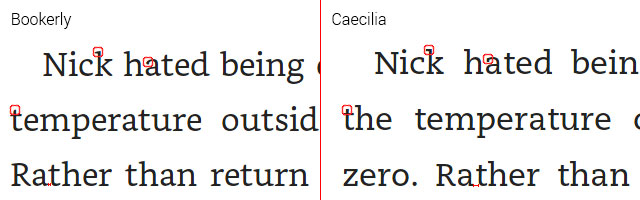
Unterschiede zwischen Bookerly (links) und Caecilia (rechts). Quelldateien: Mobileread
Auch wenn es die Schriftart aktuell nur für die Fire-Tablets gibt, ist grundsätzlich durchaus zu erwarten, dass auch die dedizierten Lesegeräte in nächster Zeit um den neuen Font erweitert werden. Abgesehen vom (wie beschrieben) verfeinerten Schriftbild, sollte man sich allerdings keine Wunder davon erwarten. Zumindest nicht in Hinblick auf die Kantenschärfe, denn die ändert sich nicht. TrueType und OpenType Schriften sind vektorisiert und damit stufenlos ohne Qualitätsverlust skalierbar, was auf Caecilia und Bookerly (und auf die anderen Schriften) gleichermaßen zutrifft. Die Schriftschärfe hängt somit von der Pixeldichte ab bzw. Interpolation ab, nicht vom Font selbst.
Hinzu kommt außerdem, dass die Kantenschärfe bei den beleuchteten und mit kapazitiven Touchscreen versehenen eBook Readern ohnehin durch die Plastikfolien gemindert wird und solche Verbesserungen kaum (oder gar nicht) auffallen würden.
In jedem Fall zeigt die Einführung einer neuen Schrift, dass Amazon glücklicherweise weiterhin an einer Verbesserung des Schriftbildes arbeitet, was auch die Hoffnung ein wenig nährt, dass der Versandriese irgendwann vielleicht doch noch die seit langem erhoffte Silbentrennung einführt, die insbesondere bei deutschsprachigen Texten oftmals abgeht. Nun darf man aber erstmal gespannt sein, ob und wann Bookerly auf den Kindle eBook Readern landet.